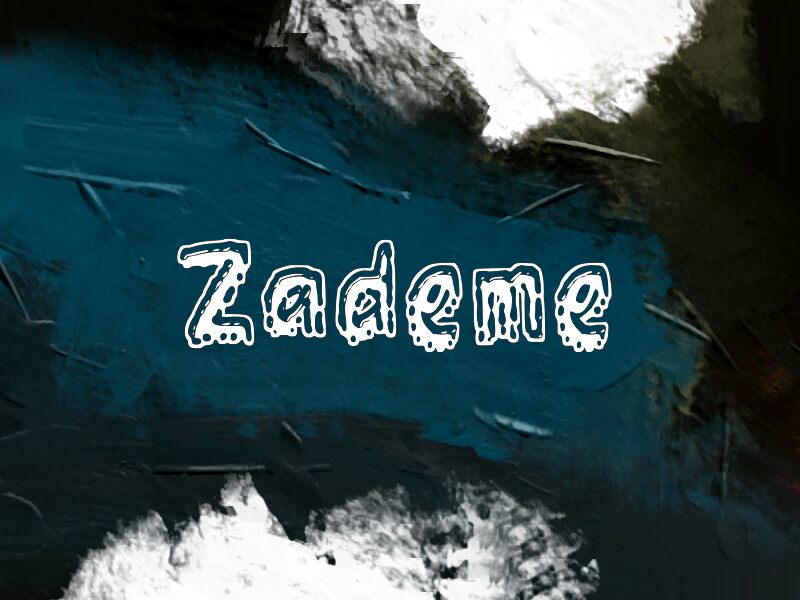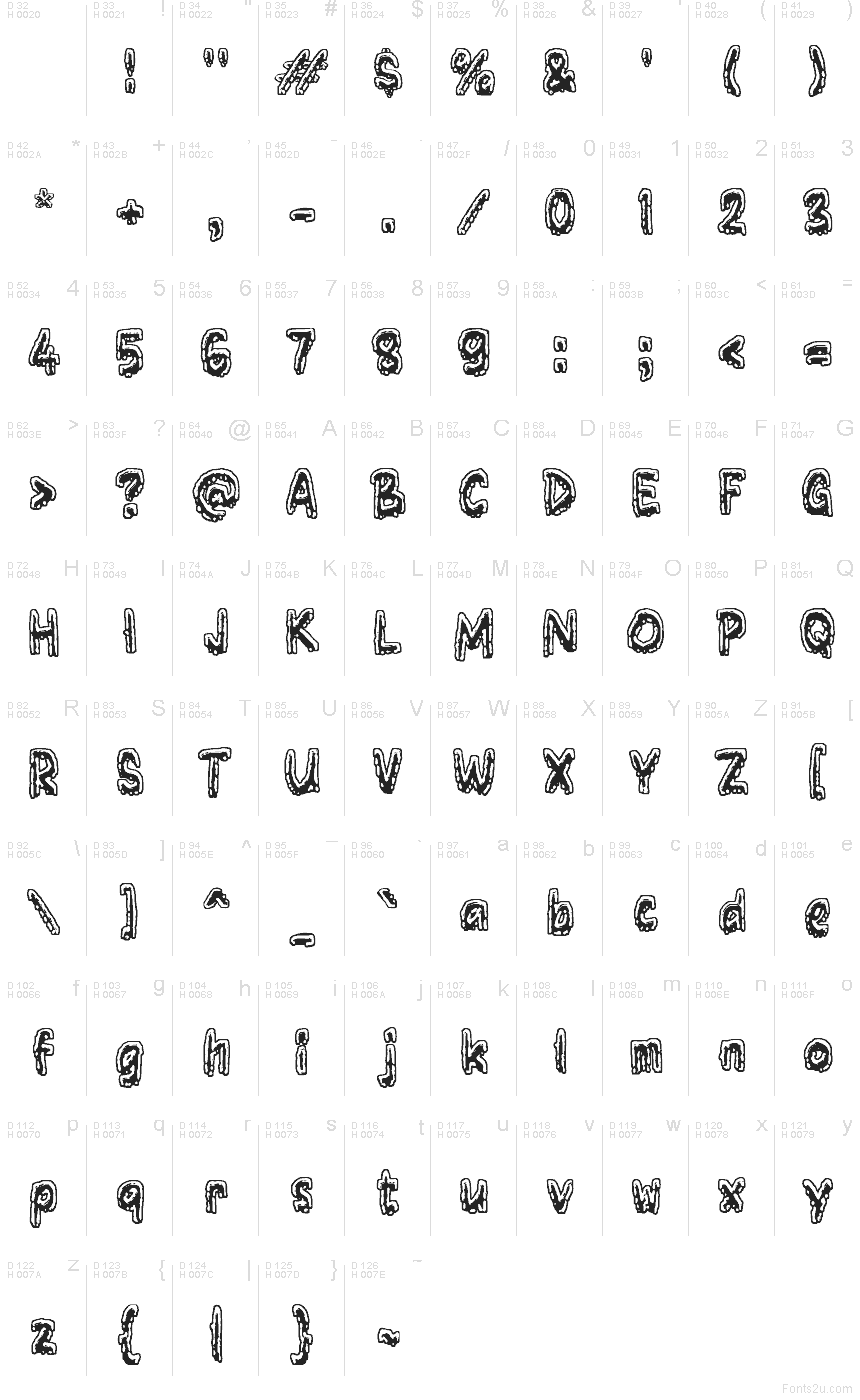
Zademe par Wep est une police de caractères gratuite de style cartoon avec des lettres qui semblent gonflées, dégoulinantes et un peu visqueuses. Ses formes arrondies et ses contours tremblants lui donnent un aspect dessiné à la main, rappelant les films de monstres, tandis que ses petits détails en forme de gouttes et ses bases affaissées rendent l'ensemble plutôt ludique que terrifiant.
Elle est idéale pour les affiches de soirées d'Halloween, les emballages de bonbons, les visuels pour enfants, les miniatures YouTube et les titres de style bande dessinée où le lettrage lui-même apporte une touche d'humour. En tant que police gratuite, Zademe fonctionne aussi parfaitement pour les titres courts, les autocollants et les essais de logos, car ses formes gonflées et fondantes assurent un impact visuel immédiat sans rien ajouter de plus.
Zademe
Présentation et spécimen de la police Zademe
Table des caractères de la police Zademe
Table des caractères de Zademe : Latin de base, page 1
Glyphes de la police Zademe — Latin de base, page 1